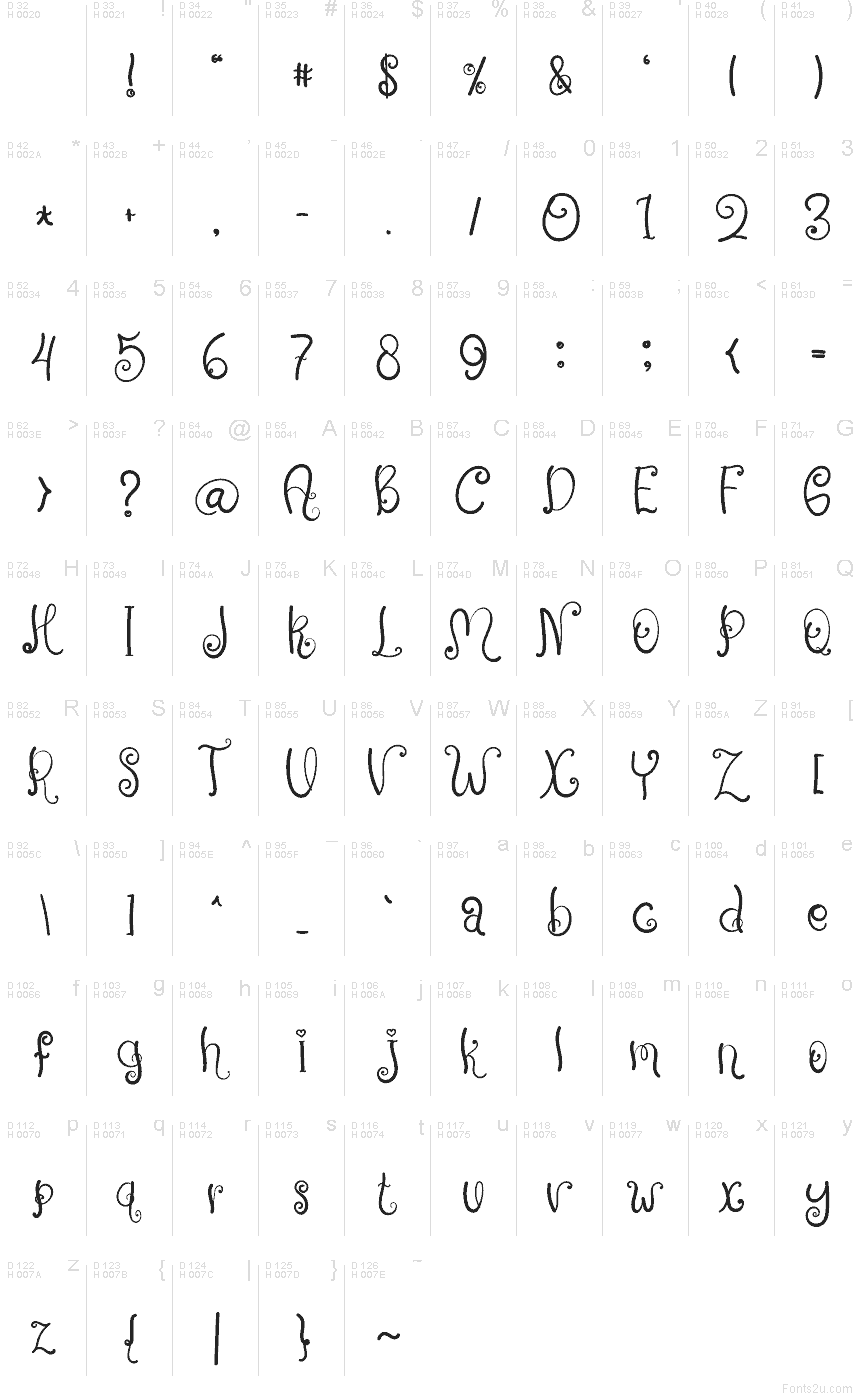
Kids Rainy je bezplatné ozdobné písmo s vysokými, smyčkovitými písmeny a lehkou roztěkaností ručně psaného písma. Dlouhé tahy se stáčejí zpět do tvarů a drobné spirálovité detaily dodávají abecedě živý namísto uhlazeného vzhledu. Srdcový akcent podtrhuje jeho dětský šarm.
Smyčky mohou připomínat načmárané mraky, kapky deště a jednoduchou linkovou kresbu na dětských obalech, pozvánkách na oslavy nebo třídních plakátech. V obrázkových knihách a časopisech pro děti se písmo může stát součástí samotné ilustrace, zejména u hravých názvů a jmen postav.
Kids Rainy
Nur Edi Prayitno